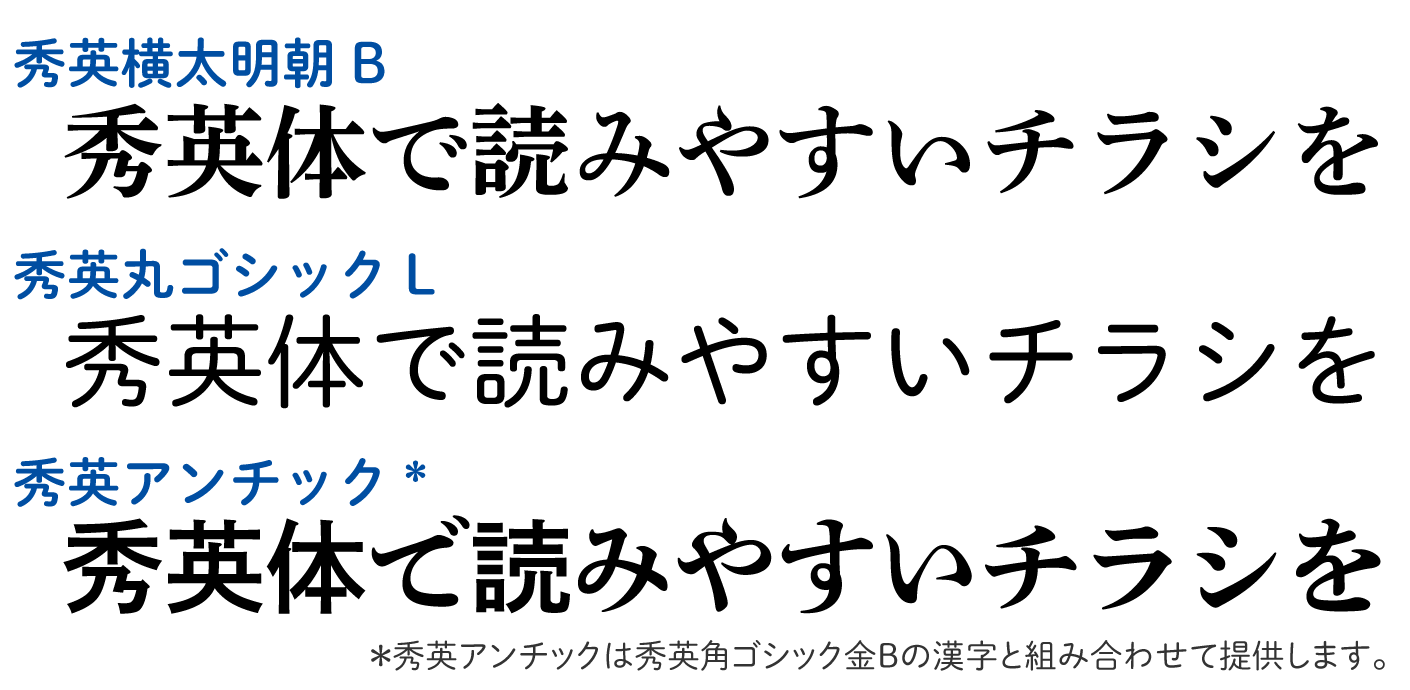
今回提供する「秀英体」3書体
Ver.14」と同様の「秀英横太明朝B」「秀英丸ゴシックL」「秀英アンチック」の3書体です。
「秀英横太明朝B」は漢字の横画を太くした視認性の高い見出し用の明朝体です。「秀英丸ゴシックL」は柔らかな印象を表現できます。「秀英アンチック」はポスターで用いても目立つユニークな書体です。
新聞や冊子、チラシなどの制作にも、秀英体をご活用ください!